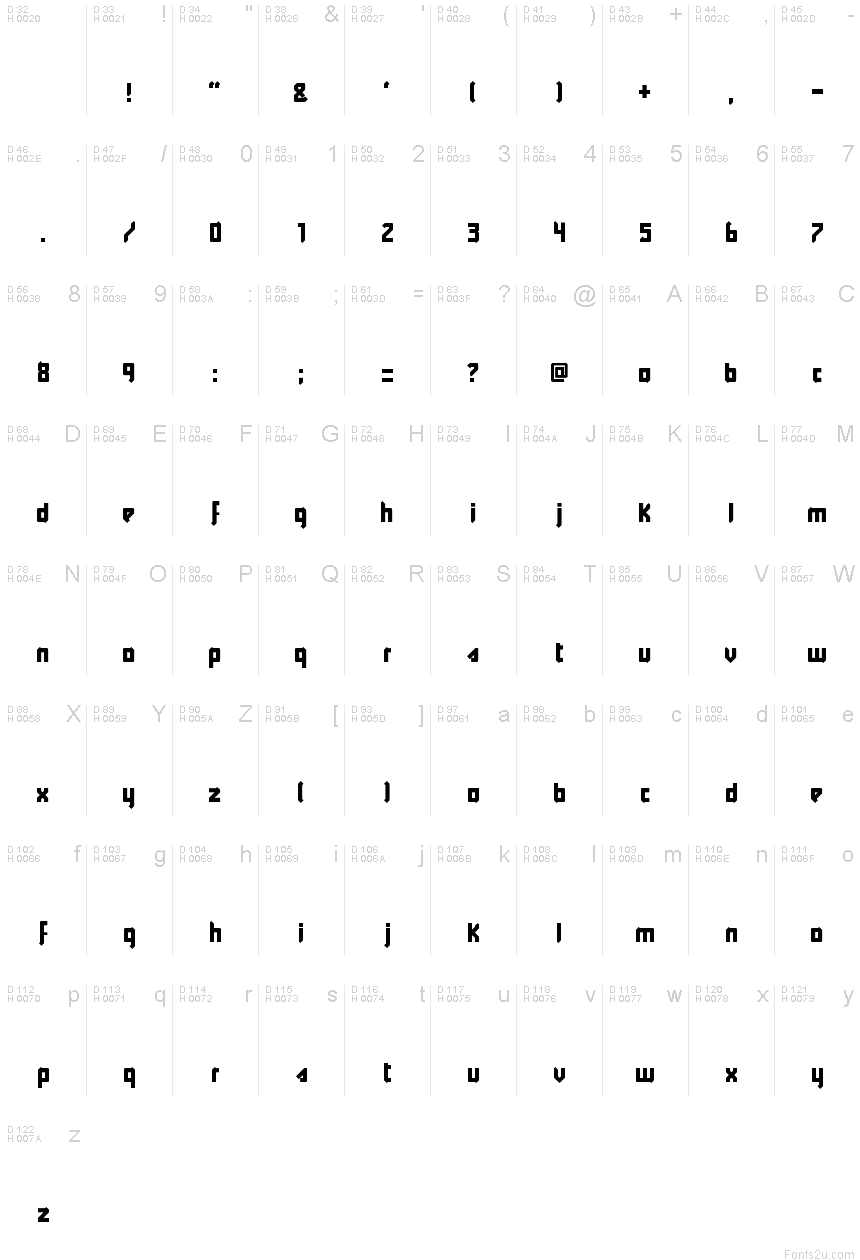
Y2K Friendly Future autorstwa Salvo Nicolosi to darmowy font typu display w klimacie Y2K techno, inspirowany estetyką konsol do gier. Litery wyglądają jak wycięte z masywnych, geometrycznych form, łącząc kwadratową ciężkość z ostrymi wcięciami i nagłymi kątami. Nadaje to krojowi klimat science-fiction z przełomu tysiącleci, jednocześnie unikając sterylnego, zbyt wygładzonego wyglądu.
Idealnie sprawdzi się w tytułach na plakatach, oprawie graficznej muzyki, grafikach do gier, ulotkach i w brandingu streetwearowym, gdzie jego urywany, cyfrowy rytm pozwala szybko przykuć uwagę. Jako darmowy font, świetnie nadaje się również do napisów na okładkach, plansz tytułowych czy krótkich haseł typu logo, zwłaszcza gdy szukasz kompaktowego, futurystycznego akcentu z lekkim pazurem.